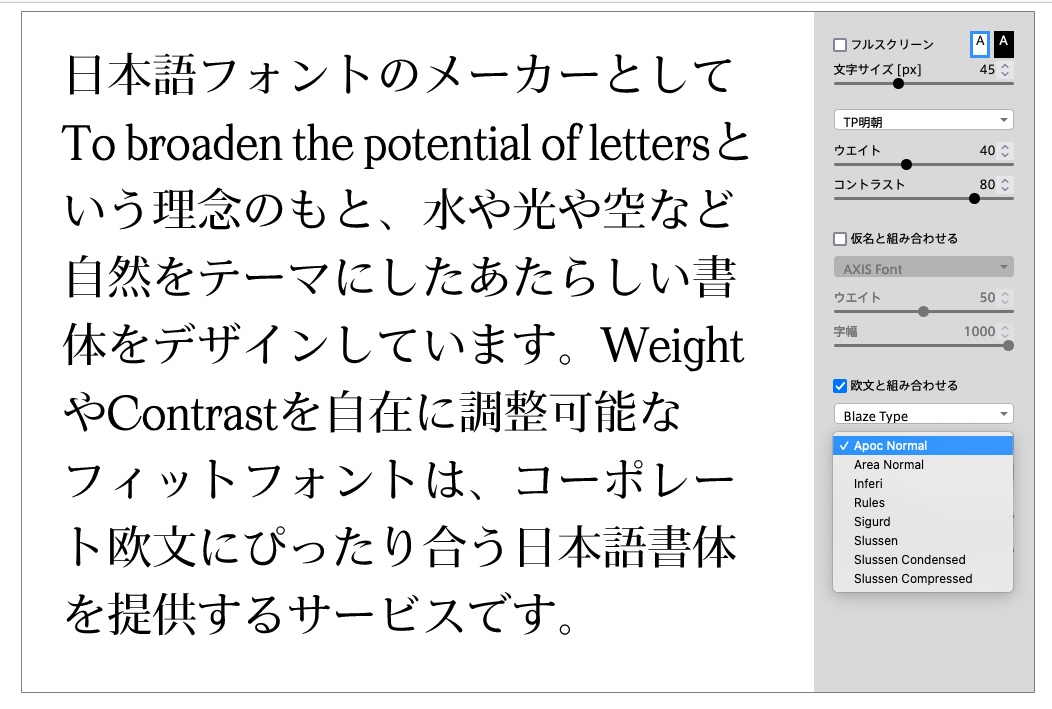
タイププロジェクトがフィットフォントサービスの欧文フォントにBlaze Typeの6ファミリーを追加
タイププロジェクトは、2022年8月4日に、フィットフォントサービスに、新しく「Blaze Type(ブレイズタイプ)」の欧文フォントを追加したことを発表した。
多岐にわたるフォントで多くの言語に対応し、さまざまな代替文字やスタイルとウエイトの幅広いフォントファミリーを展開している「Blaze Type」は、フランス リヨンに拠点を置く独立系タイプファウンダリーで、コンテンポラリーなリテールフォントとカスタムフォントの制作に力を入れている。
タイププロジェクトでは、フィットフォントサービスとして、ウエイトやコントラスト、字幅、フトコロ軸を変更した場合でも、書体を常に理想的な設計に保つシステムを開発し、ダイナミックに変化しながらもデザインの一貫性と品質を保持することを実現しており、AXIS FontやTP明朝、TPスカイなど、タイププロジェクトのそれぞれの書体で500から10,000以上のバリエーションで、他社の欧文フォントに合わせて調節することで和文と欧文の適正なバランスを得ることを可能にしている。
フィットフォントサービスに追加したBlaze Typeの欧文フォントは、「ヨハネの黙示録」からインスピレーションされた、組合せ例:Apoc + TP明朝フィットフォントを得たApocを始め、Area、Inferi、Rules、Sigurd、Slussenの6ファミリーで、全51フォントとなる。
▼組合せ例:Apoc + TP明朝フィットフォント
Blaze Typeの創立者でタイプデザイナーのMatthieu Salvaggio氏は、「以前からアジアの、とりわけ日本の会社と関わりたいと思っていました。TPスカイの核心を突いたデザインはエレガントで安定感があり、とても好きです。フィットフォントのようなサービスを提供するというのはすばらしい発想だと思います。このサービスに参加できることが本当に光栄で嬉しく思います」と述べている。